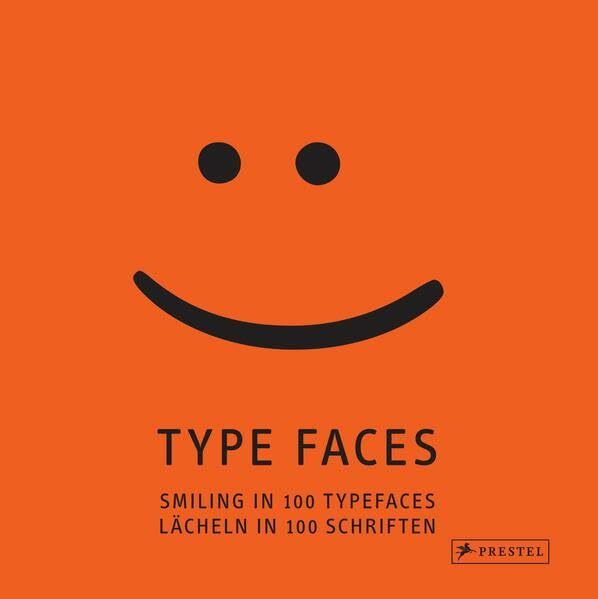
Type Faces: Smiling in 100 Typefaces – Lächeln in 100 Schriften
"Type Faces: Smiling in 100 Typefaces – Lächeln in 100 Schriften" von Kai Kullen ist ein kreatives und einzigartiges Buch, das die Welt der Typografie auf spielerische Weise erkundet. In diesem Buch werden verschiedene Schriftarten verwendet, um lächelnde Gesichter zu gestalten. Jede Doppelseite präsentiert eine andere Schriftart, wobei typografische Elemente geschickt eingesetzt werden, um emotionale Ausdrücke darzustellen. Das Buch lädt Leser dazu ein, die Vielfalt und den Charakter von Schriftarten aus einer neuen Perspektive zu betrachten. Es ist sowohl für Design-Enthusiasten als auch für alle, die Freude an Typografie haben, eine inspirierende und unterhaltsame Lektüre.